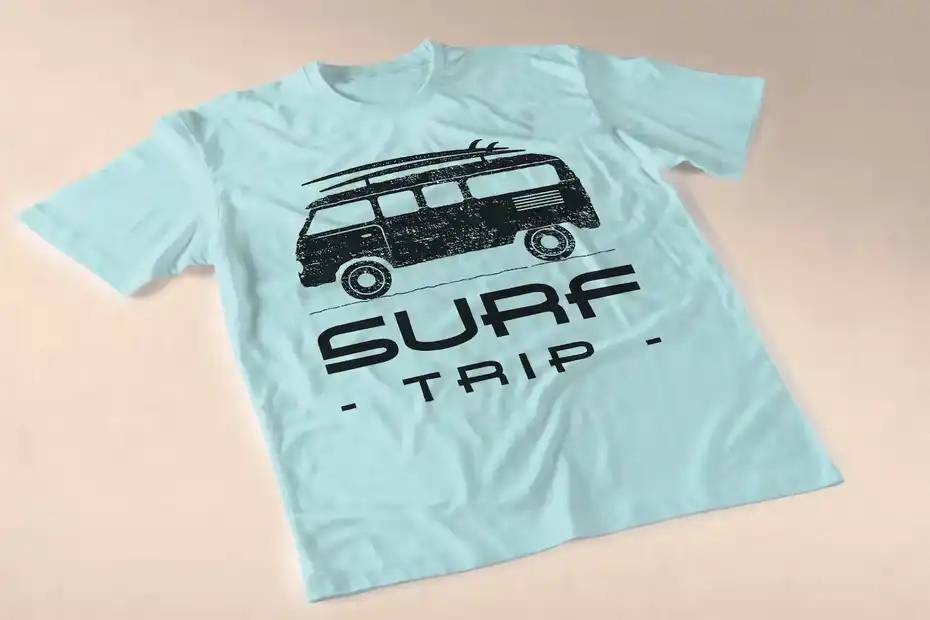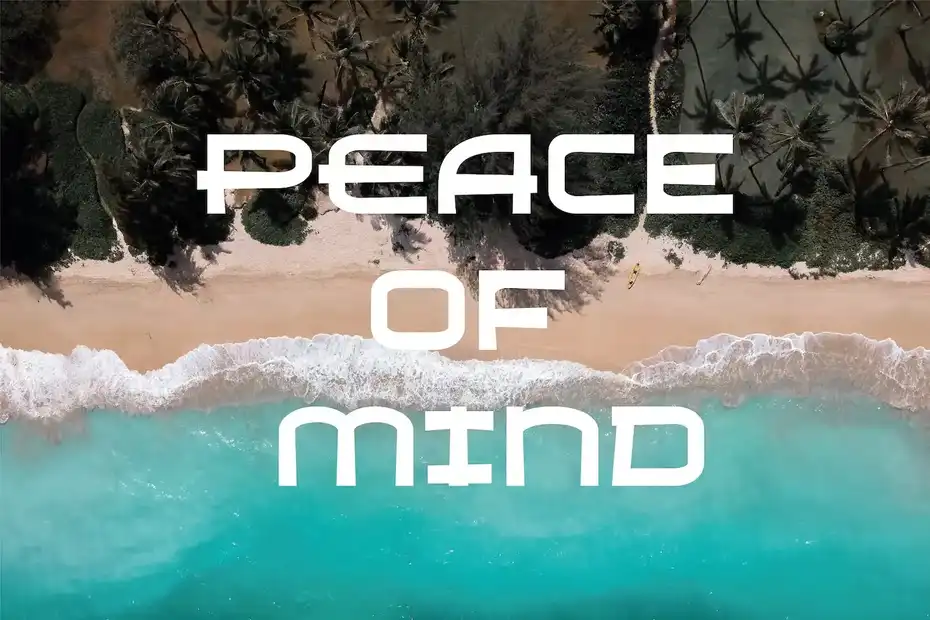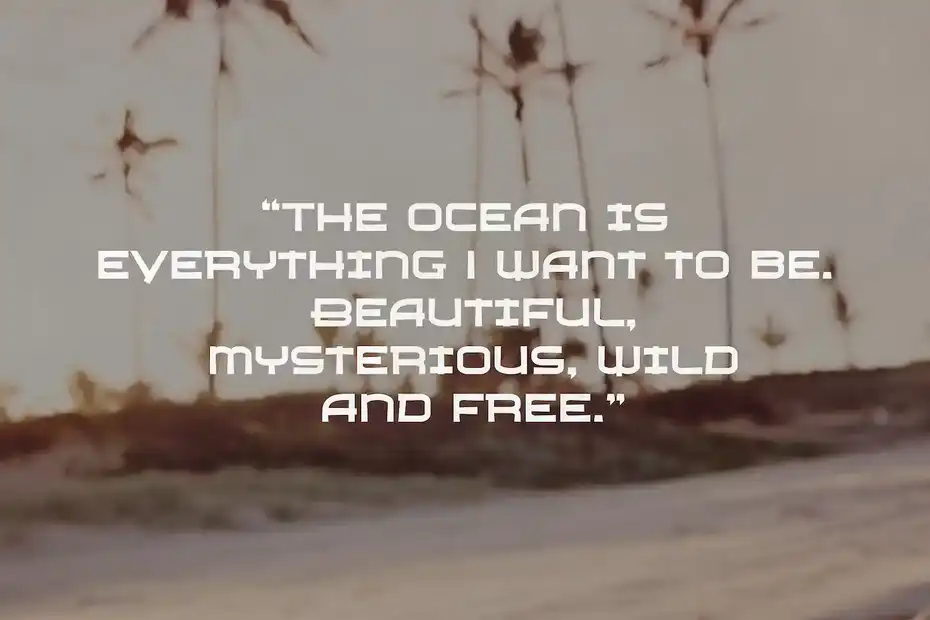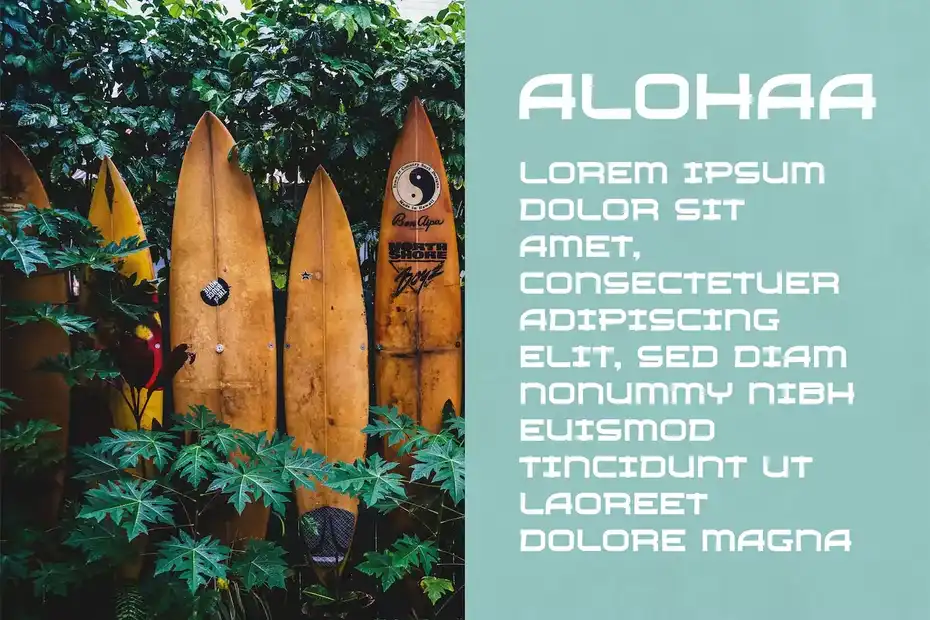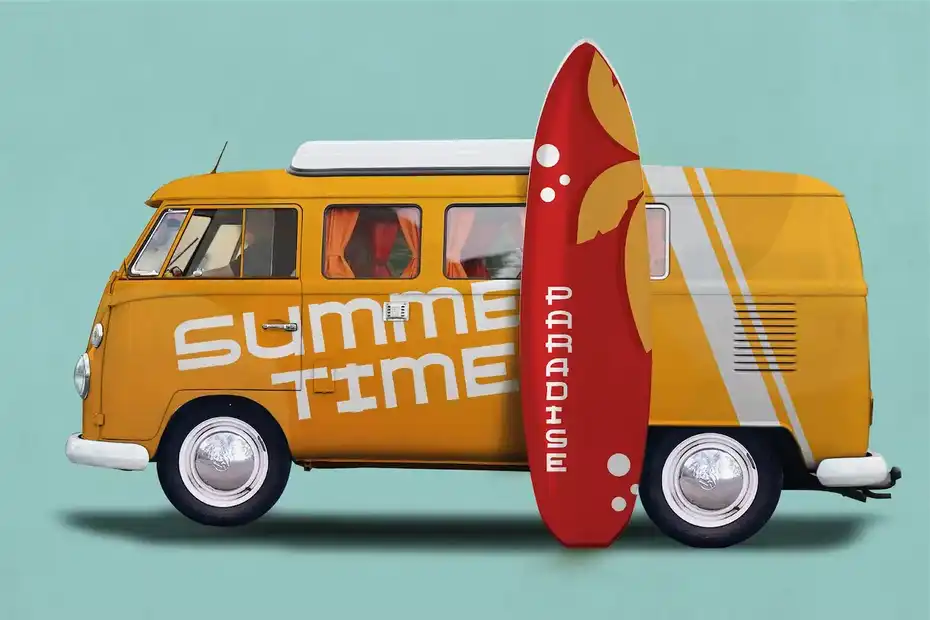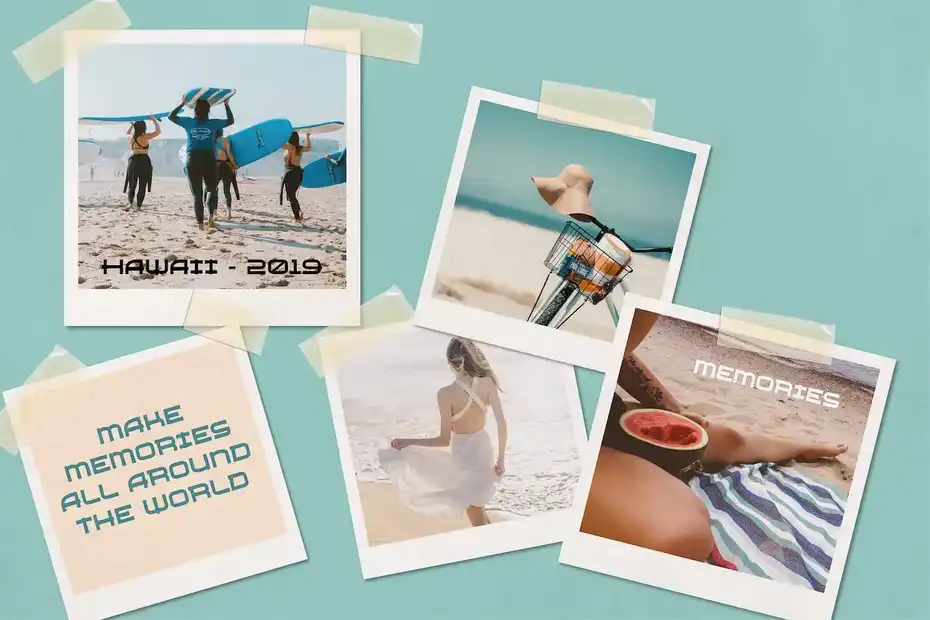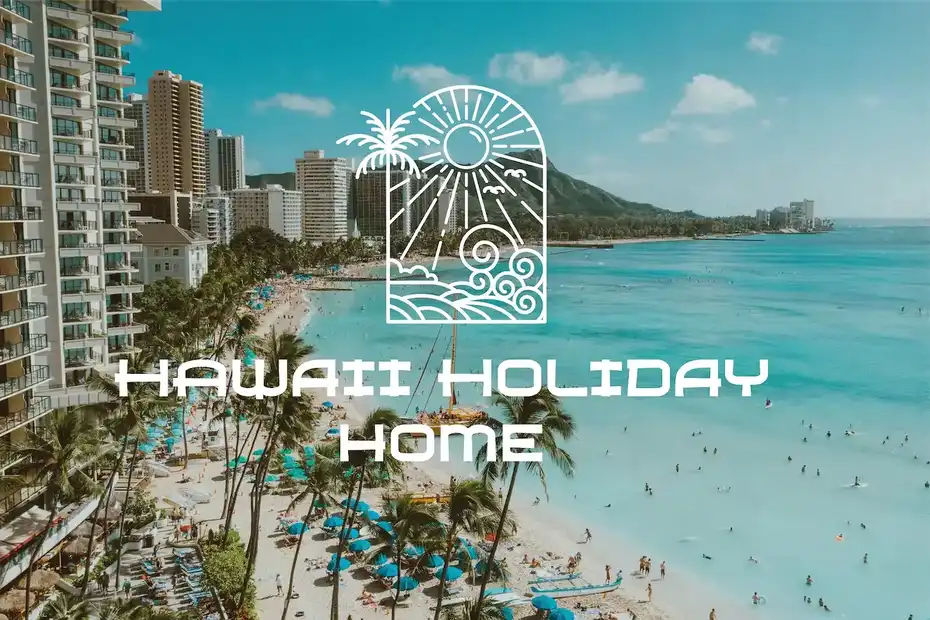
دانلود فونت انگلیسی Boomerang – Hawaiian Typeface
فونت انگلیسی Boomerang – Hawaiian Typeface : این مجموعه شامل یک فونت گرافیکی است که برای تبلیغات، برندینگ، کاور آلبوم، پوشاک، کارت‌ ویزیت، آگهی‌، دعوت‌ نامه‌ ها، منو ها، کالا ها، بسته‌ بندی، وب، تابلو های تبلیغاتی و غیره مناسب میباشد.
• عنوان مجموعه: Boomerang – Hawaiian Typeface
فونت انگلیسی Boomerang - Hawaiian Typeface - 1
فونت انگلیسی Boomerang - Hawaiian Typeface - 3
فونت انگلیسی Boomerang - Hawaiian Typeface - 5
فونت انگلیسی Boomerang - Hawaiian Typeface - 7
فونت انگلیسی Boomerang - Hawaiian Typeface - 9
فونت انگلیسی Boomerang - Hawaiian Typeface - 11
فونت انگلیسی Boomerang - Hawaiian Typeface - 13
فونت انگلیسی Boomerang - Hawaiian Typeface - 15
فونت انگلیسی Boomerang - Hawaiian Typeface - 17